45 แบบอักษรแฟชั่นที่ดีที่สุดในปี 2023 (ฟรีและพรีเมียม)
ตั้งแต่ฟอนต์ serif ที่สง่างามไปจนถึงฟอนต์ sans-serif สมัยใหม่ เราได้คัดสรรรายการฟอนต์ที่จะยกระดับโปรเจกต์แฟชั่นของคุณไปอีกขั้น คุณทราบหรือไม่ว่าการรวมแบบอักษรที่เหมาะสมเข้ากับการออกแบบของคุณอาจมีผลกระทบอย่างมากต่อการรับรู้ของผู้ชมที่มีต่อแบรนด์ของคุณ การเลือกฟอนต์ที่เหมาะสมไม่ใช่แค่เรื่องของความสวยงามเท่านั้น แต่ยังส่งผลต่อข้อความโดยรวมที่งานออกแบบของคุณสื่อถึงอีกด้วย
แบบอักษรแฟชั่นระดับพรีเมียมที่ดีที่สุด
แฟชั่น
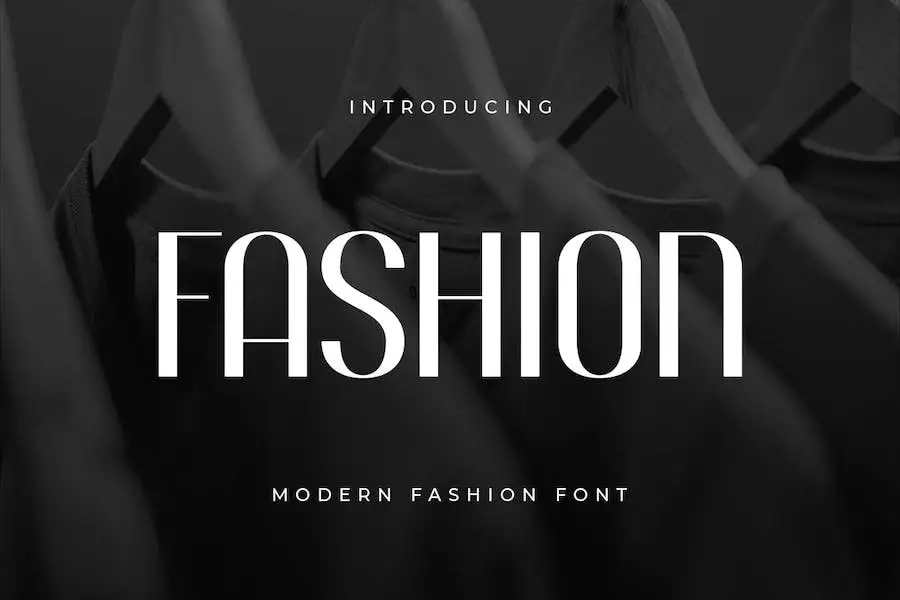
Fashion คือแบบอักษร San Serif แบบใหม่ที่ออกแบบมาสำหรับพาดหัวข่าว ชื่อเรื่อง และความต้องการด้านการพิมพ์ที่โดดเด่นอื่นๆ ฟอนต์ถูกสร้างขึ้นด้วยตัวอักษรที่สวยงามซึ่งเพิ่มความหลากหลายให้กับงานของคุณ เหมาะอย่างยิ่งสำหรับการเพิ่มสไตล์และให้ความรู้สึกทันสมัยที่ไม่ซ้ำใคร แบบอักษรได้รับการออกแบบมาเป็นพิเศษเพื่อทำให้โครงการของคุณโดดเด่นและแสดงแนวคิดหลักของคุณ
แฟชั่นเป็นตัวเลือกที่สมบูรณ์แบบสำหรับนักออกแบบกราฟิกที่กำลังมองหาแบบอักษรที่เพิ่มลักษณะเฉพาะและสไตล์ให้กับงานของพวกเขา ด้วยความรู้สึกที่ทันสมัยไม่เหมือนใคร ฟอนต์แฟชั่นของ Google นี้จึงเหมาะสำหรับโครงการใดๆ ก็ตามที่ต้องการตัวพิมพ์ที่โดดเด่น ไม่ว่าคุณจะต้องการออกแบบปกนิตยสารหรือสร้างส่วนหัวของเว็บไซต์ Fashion คือตัวเลือกที่สมบูรณ์แบบ
โมดิสแฟชั่น
Modis Fashion เป็นส่วนเพิ่มเติมที่โดดเด่นสำหรับนักออกแบบที่กำลังมองหา Adobe Fashion Font ขั้นสูงเพื่อปรับปรุงงานศิลปะของพวกเขา แบบอักษรนี้ไม่เหมือนใครและใช้งานง่ายสำหรับทุกอย่างตั้งแต่ป้ายชื่อ เสื้อผ้า ฉากภาพยนตร์ โปสเตอร์ ปกอัลบั้ม โลโก้ และอื่นๆ อีกมากมาย
โมเบิร์นแฟชั่น
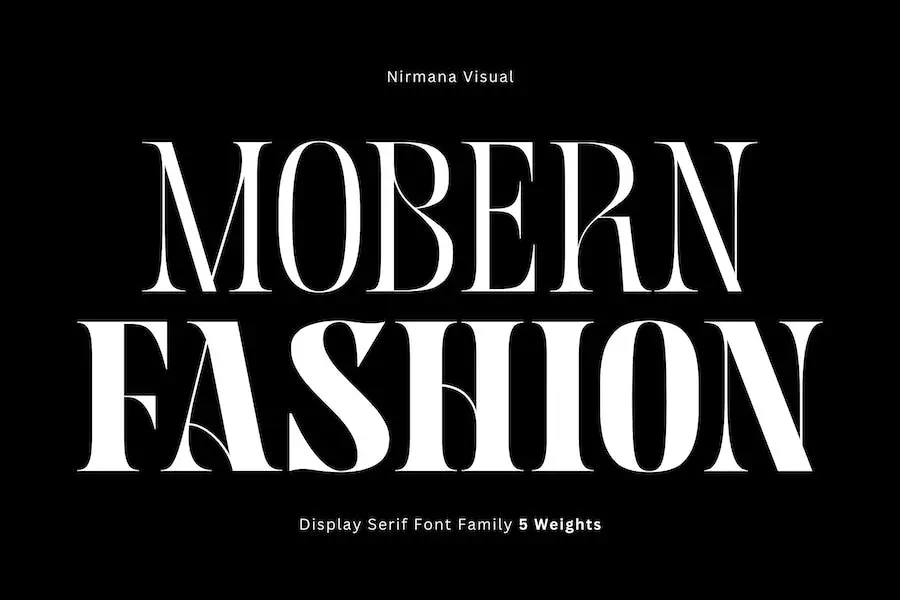
Mobern Fashion เป็นตระกูล sans-serif ที่ไม่เหมือนใครและขี้เล่น ซึ่งมาพร้อมกับน้ำหนักที่แตกต่างกันห้าแบบ มีสองรูปแบบตัวอักษร: .otf และ .ttf นอกจากนั้น ยังมีไฟล์ .woff ตระกูลฟอนต์นี้ช่วยสร้างความกลมกลืนของตัวพิมพ์ที่สวยงาม ซึ่งสามารถนำไปใช้กับโครงการออกแบบที่หลากหลาย เช่น โลโก้ การสร้างแบรนด์ โพสต์บนโซเชียลมีเดีย โฆษณา และการออกแบบผลิตภัณฑ์
การออกแบบของ Mobern Fashion มีความหลากหลายมาก ทำให้สามารถนำไปใช้กับโครงการออกแบบได้หลากหลาย นอกจากนี้ ฟอนต์แฟชั่นของ Word นี้ยังมีรูปแบบตัวอักษรที่สวยงามกลมกลืนซึ่งจะทำให้งานออกแบบของคุณโดดเด่นอย่างแน่นอน ด้วยฟอนต์นี้ คุณสามารถเพิ่มป๊อปที่จำเป็นมากให้กับโปรเจกต์การออกแบบของคุณได้
เพิ่มแฟชั่น
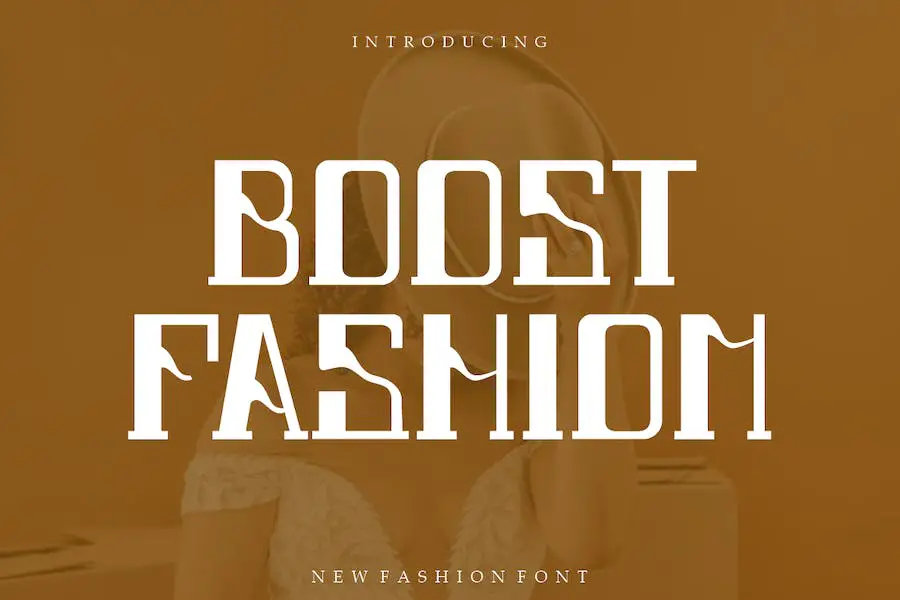
Boost Fashion เป็นฟอนต์แฟชั่นสมัยใหม่ที่เพิ่มสัมผัสที่โดดเด่นและแท้จริงให้กับโปรเจกต์การออกแบบใดๆ แบบอักษรนี้เหมาะสำหรับสื่อการสร้างแบรนด์และการตลาด เช่น โลโก้ ภาพพิมพ์เสื้อยืด และอื่นๆ คุณลักษณะที่หลากหลายและเป็นเอกลักษณ์ทำให้โดดเด่นในบริบทต่างๆ
หมุน
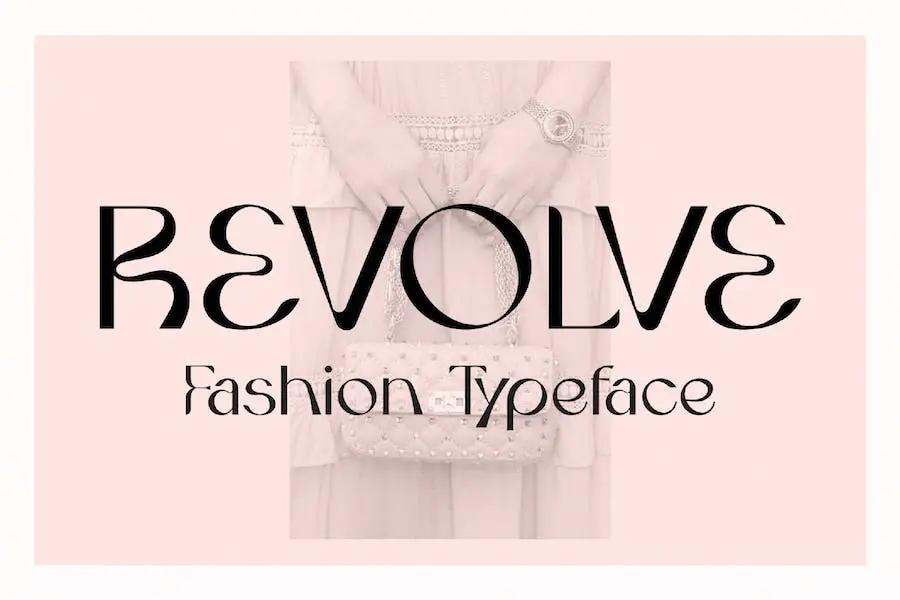
Revolve เป็นแบบอักษรที่ซับซ้อนซึ่งได้รับแรงบันดาลใจจากนิตยสารแฟชั่น ด้วยความสมดุลระหว่างเส้นหนาและเส้นบาง แบบอักษรนี้จึงเหมาะอย่างยิ่งสำหรับการสร้างงานออกแบบที่หรูหรา เหมาะอย่างยิ่งสำหรับโครงการต่างๆ รวมถึงการสร้างแบรนด์ การโฆษณา โซเชียลมีเดีย มู้ดบอร์ด บรรจุภัณฑ์ การออกแบบบรรณาธิการ หัวข้อข่าว และอื่นๆ
แบร์ลอสเซียน่า
Berlossiana เป็นฟอนต์เขียนด้วยลายมือที่น่าทึ่งซึ่งเพิ่มความสง่างามและสไตล์ให้กับโครงการออกแบบใดๆ ด้วยการสนับสนุนหลายภาษาและเว็บฟอนต์ในรูปแบบ OTF, TTF และ WOFF ทำให้ง่ายต่อการรวมเข้ากับโปรเจ็กต์ DIY ใดๆ
แบบอักษรนี้ประกอบด้วยตัวอักษร ตัวเลข เครื่องหมายวรรคตอน อักษรควบ เครื่องหมายทับ และตัวเลือกอื่นๆ ที่ช่วยให้สร้างสรรค์ได้ไม่รู้จบ ไม่ว่าคุณจะออกแบบโลโก้ เว็บไซต์ หรือโพสต์บนโซเชียลมีเดีย Berlossiana เป็นตัวเลือกที่สมบูรณ์แบบสำหรับการออกแบบแนวแฟชั่น รับแรงบันดาลใจและยกระดับเกมการออกแบบของคุณด้วย Berlossiana นี่เป็นแบบอักษรแฟชั่นที่ดีสำหรับ Figma
แฟชั่นโมดิช
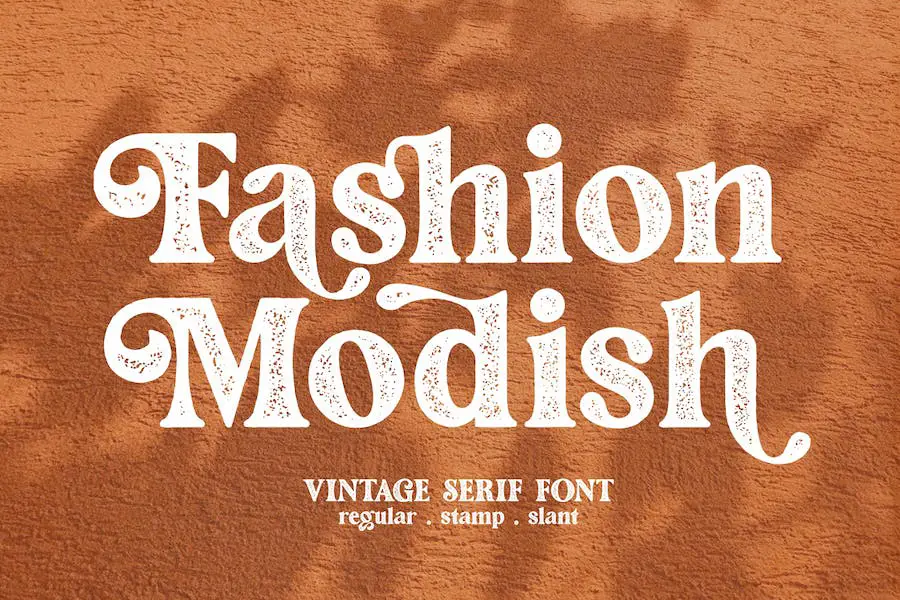
Fashion Modish เป็นส่วนเสริมที่สมบูรณ์แบบสำหรับโปรเจ็กต์ล่าสุดของคุณ สไตล์วินเทจที่โดดเด่นและทันสมัยพร้อมเอฟเฟกต์ตราประทับช่วยเพิ่มความรู้สึกวินเทจที่โดดเด่น
ด้วยฟอนต์ที่ไม่ซ้ำกัน 11 แบบ ฟีเจอร์ OpenType เช่น ลิเกเจอร์และสไตลิสสำรอง และแม้แต่ฟอนต์บนเว็บ ฟอนต์ที่สวยงามนี้จึงเหมาะสำหรับหนังสือพิมพ์ โปสเตอร์ โลโก้ เครื่องเขียน พาดหัวข่าว ป้าย หนังสือ นิตยสาร และอื่นๆ Fashion Font นี้เหมาะสำหรับศิลปะรอยสัก